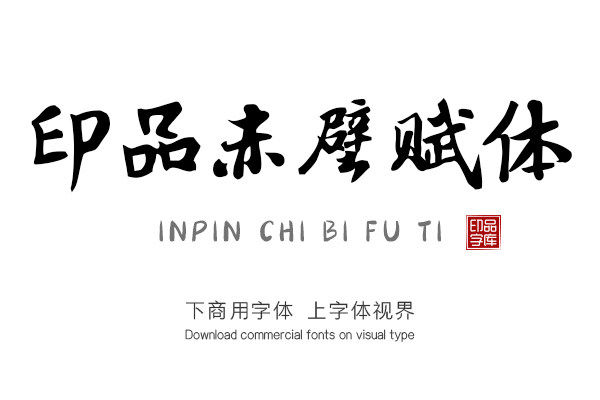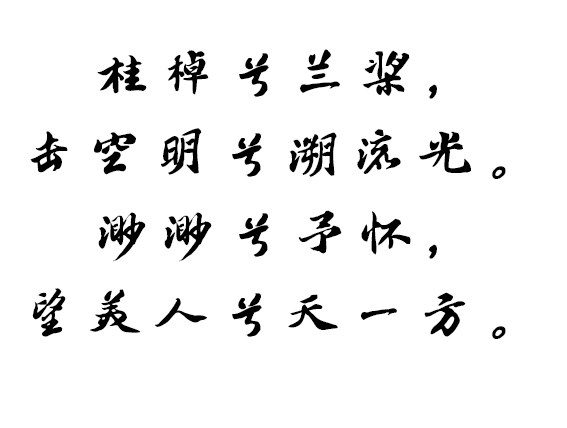
印品赤壁赋体源于北宋文学家苏轼创作的一篇赋,全赋在布局与结构安排中映现了其独特的艺术构思,情韵深致、理意透辟,有很高的文学地位。见字如晤,愿后人都能记住这位伟大的文学家。
这款手写体粗犷硬朗的线条,使笔画和转角处都显得非常干脆,横轻竖重,轻重搭配,同样给人很强的韵律感;字体朴拙厚重,平和中正,端庄娟秀,结体扁平,字体气势突出,有很强的视觉冲击力,且节奏分明,个性张扬,带给人视觉上的震撼感。这款字体适用于游戏,LOGO,影视动漫等场景中。